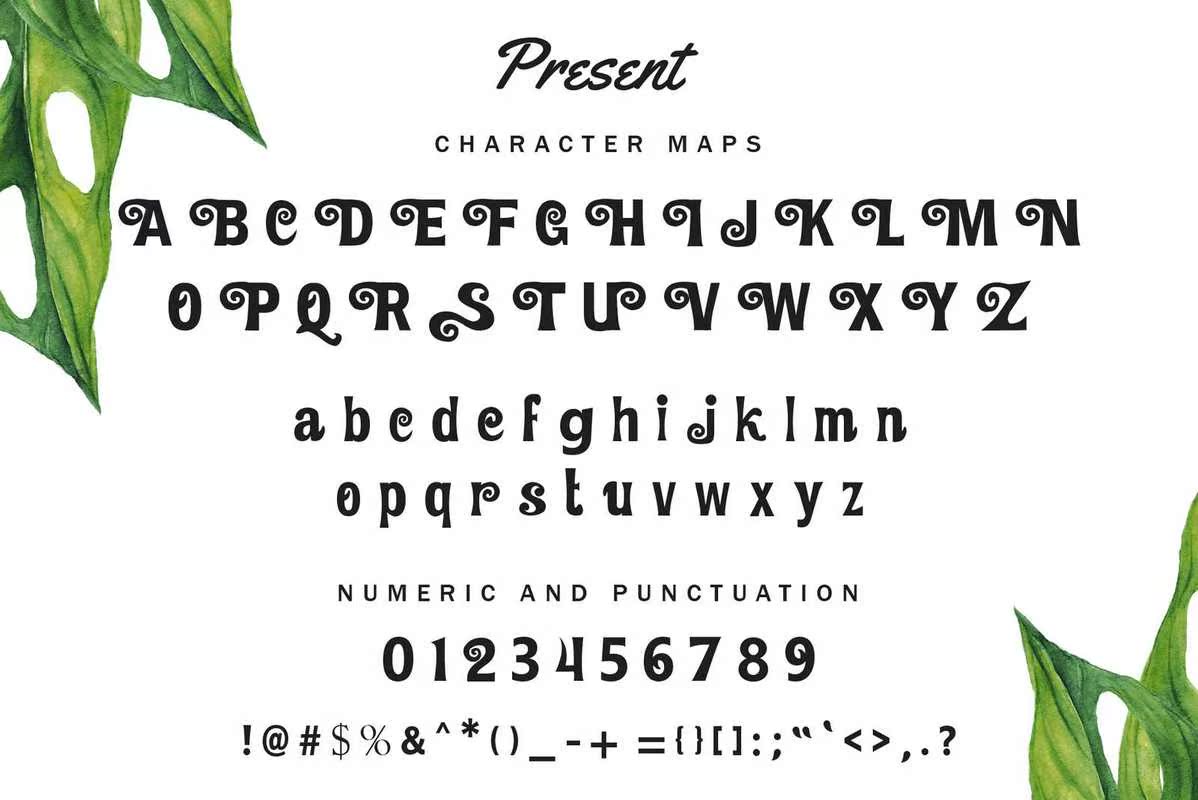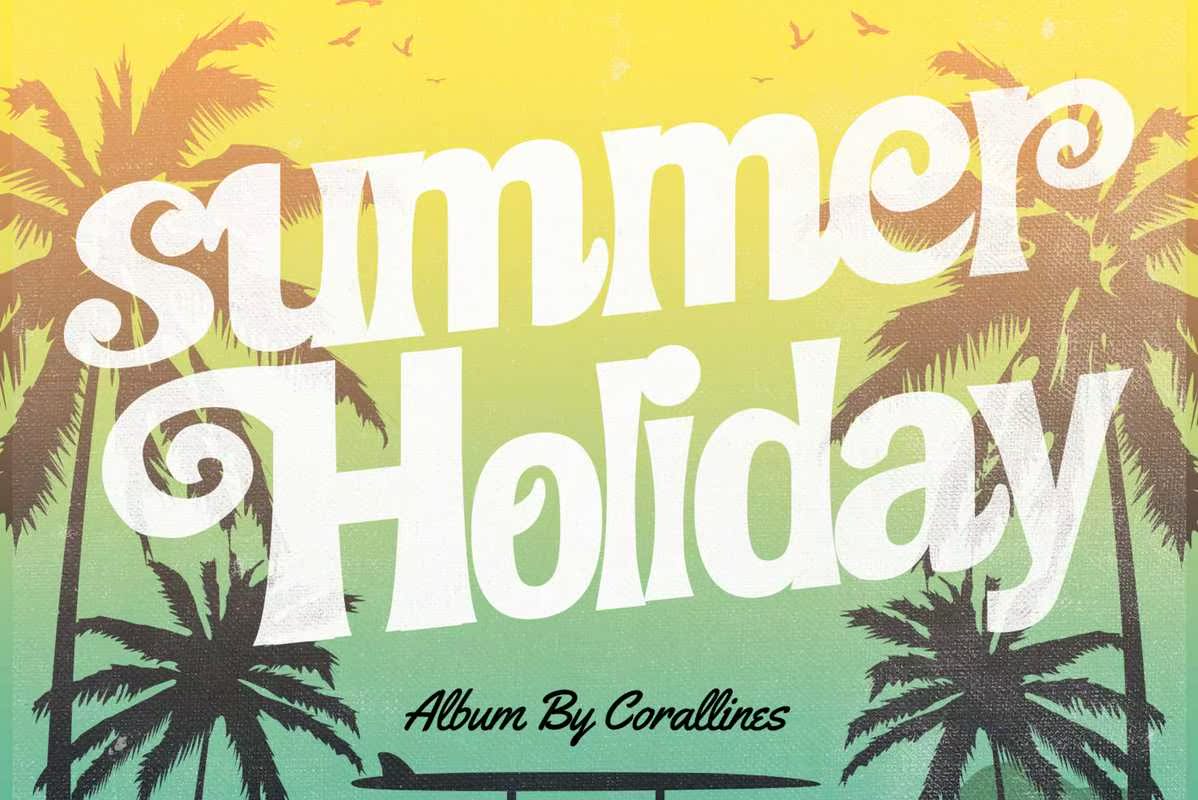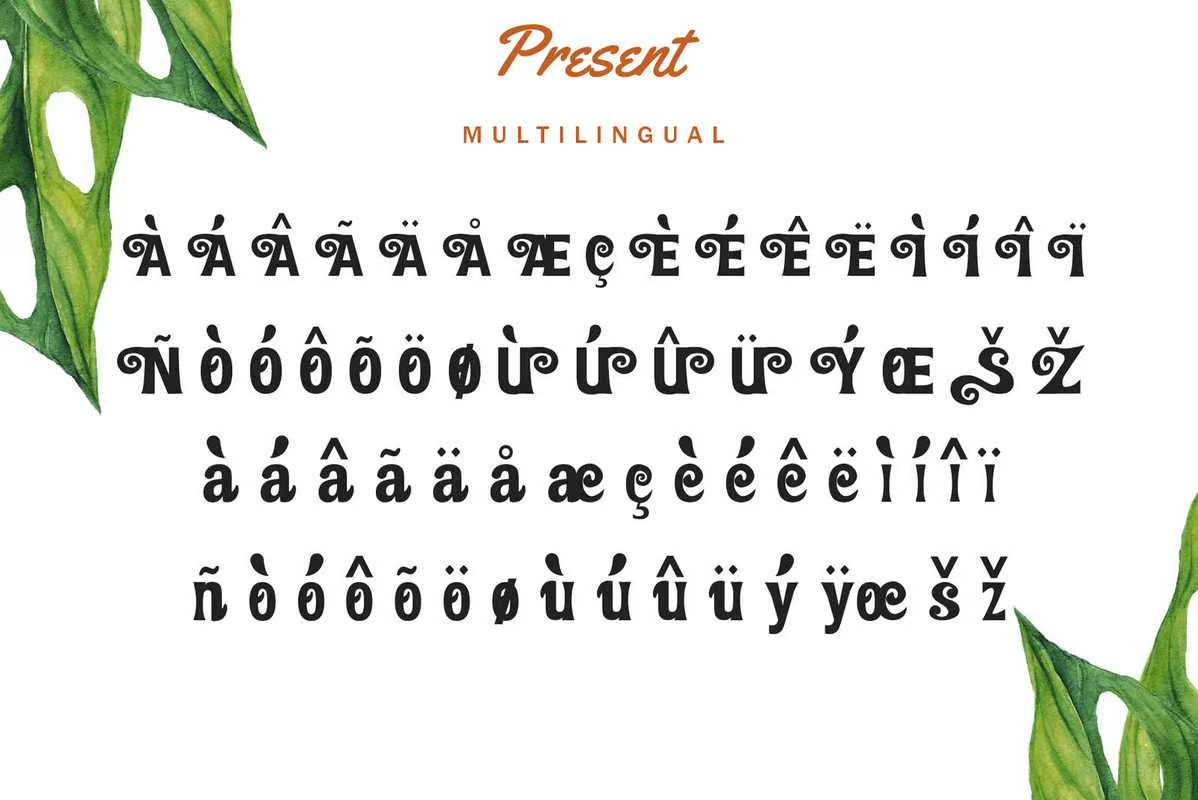
Sunflower Display FontTypeface简介新版本,Sunflower Display FontTypeface。此类型集适用于品牌徽标、邀请函、问候卡或任何类型的项目。此类型集具有多种语言功能和样式变体,可进一步增强您作品的审美观。简介新版本,Sunflower Display FontTypeface。此类型集适用于品牌徽标、邀请函、,欢迎卡,或任何类型的项目。具有多种语言功能和样式变化,这种字体将进一步增强您工作的时尚感。